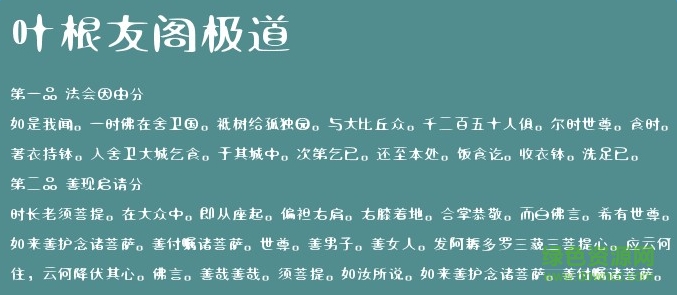
葉根友閣極道字體是一款適用于古典藝術(shù)設(shè)計(jì)的電腦字體,這款字體把中國(guó)道教文化完美融入其中,感興趣的朋友歡迎來綠色資源網(wǎng)下載使用。
葉根友閣極道字體是一款具有中國(guó)道教文化元素的字體,字的筆畫圓中有正,字正方圓,具有禪文化和道家文化與書法文化是結(jié)合。
葉根友閣極道字體是一款極具中國(guó)歷史文化的氣息,這款字體融合了中國(guó)道教文化,非常有特色。